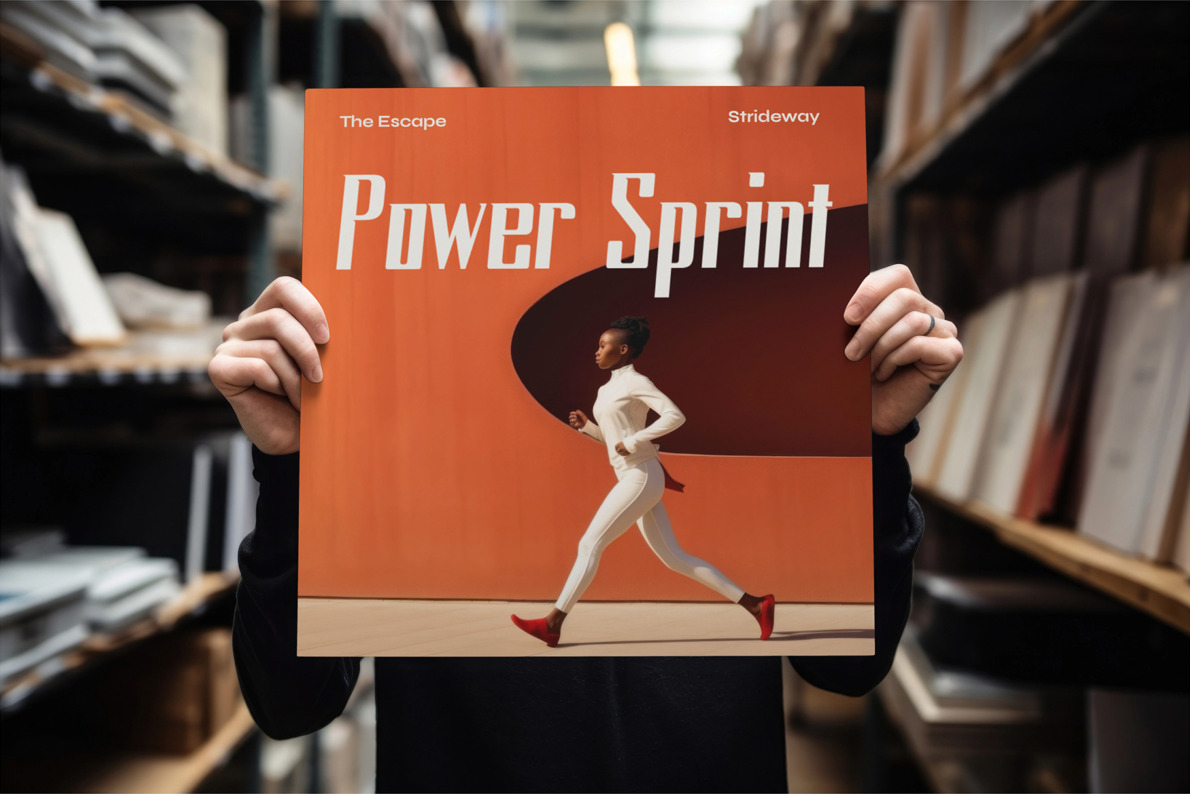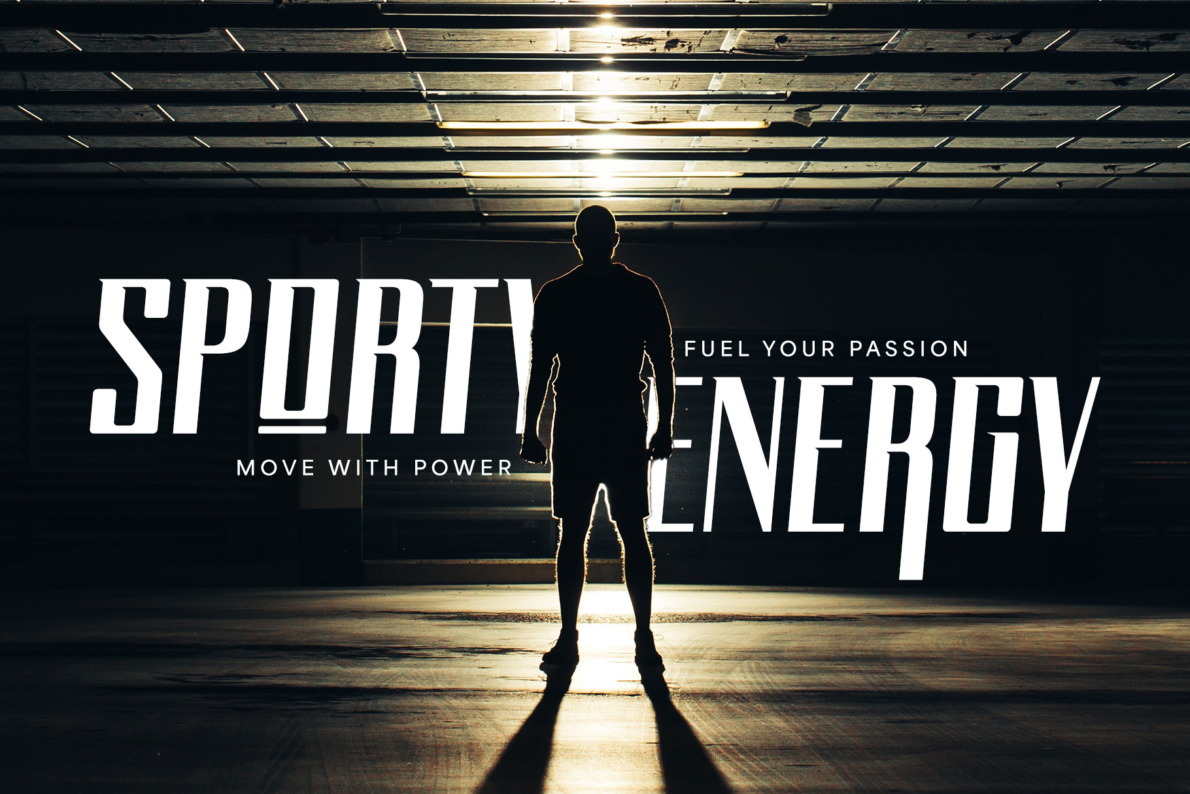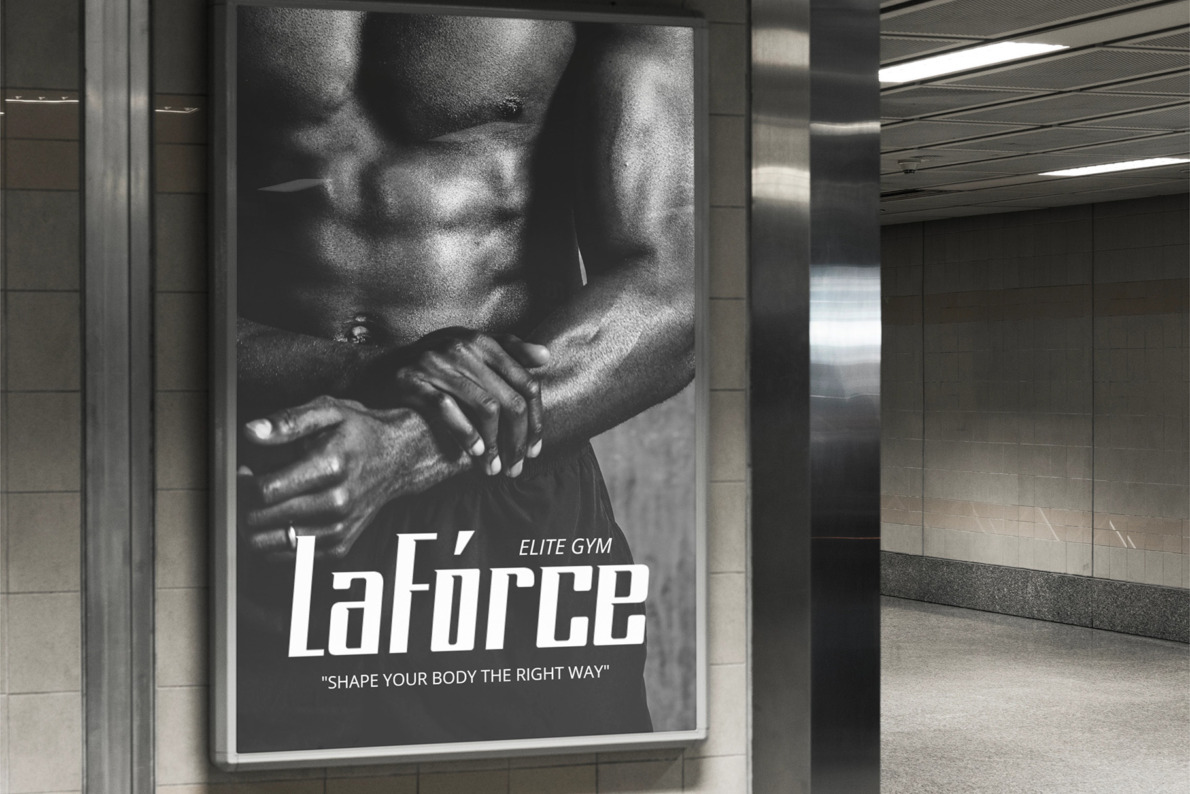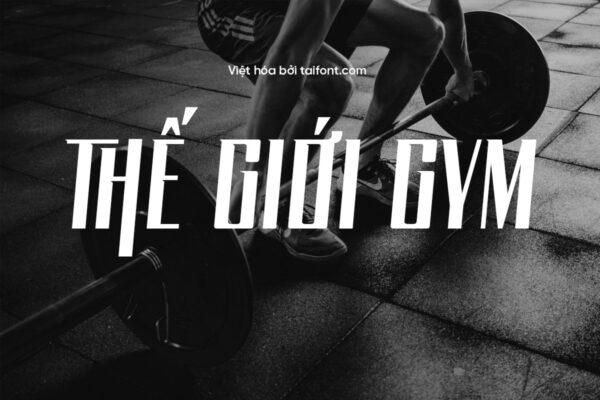
Giới thiệu về Font TF Bockley Việt hóa
TF Bockley Việt hóa là một font chữ không chân (sans-serif) nổi bật với thiết kế nghiêng, mạnh mẽ và đầy năng lượng, lý tưởng để truyền tải sự năng động, tốc độ và tinh thần thể thao. Font này gợi cảm giác về sự chuyển động tiến lên, quyết tâm và sức mạnh, rất phù hợp với các thiết kế mang tính thể thao và hiệu suất cao.
Với đặc điểm là nét nghiêng ấn tượng, độ đậm vừa phải và phong thái mạnh mẽ, Bockley là lựa chọn hoàn hảo cho các thiết kế muốn truyền tải sự năng động, cá tính và niềm đam mê:
- Thiết kế Gym và Thể thao: Hoàn hảo cho các poster, banner quảng cáo phòng gym, trung tâm thể hình, sự kiện thể thao, hoặc các thương hiệu liên quan đến thể thao như trang phục, dụng cụ, hoặc phụ kiện. Font này giúp tạo không khí sôi động, cạnh tranh và mạnh mẽ, thúc đẩy tinh thần tập luyện và chiến thắng.
- Thiết kế logo và nhận diện thương hiệu: Lý tưởng cho logo các câu lạc bộ thể thao, đội tuyển, hoặc các thương hiệu muốn thể hiện sự mạnh mẽ, tốc độ và tính cạnh tranh.
- In ấn: Đảm bảo khả năng đọc tốt ngay cả ở kích thước lớn, và tạo hiệu ứng thị giác mạnh mẽ khi in trên áo thun, biểu ngữ, hoặc các sản phẩm khác.
Với TF Bockley Việt hóa, bạn có thể dễ dàng thổi hồn thể thao, sự năng động và cá tính vào các thiết kế, tạo ra những sản phẩm không chỉ đẹp mắt mà còn đầy cảm xúc và sức hút đặc biệt.
Font Việt hóa TF Bockley – Phong chữ gym